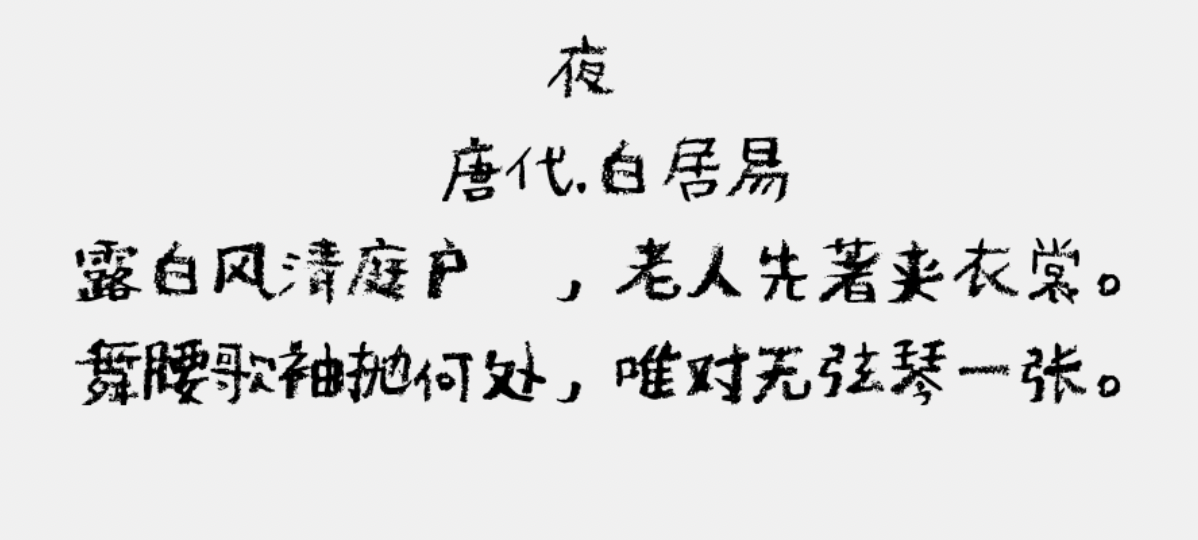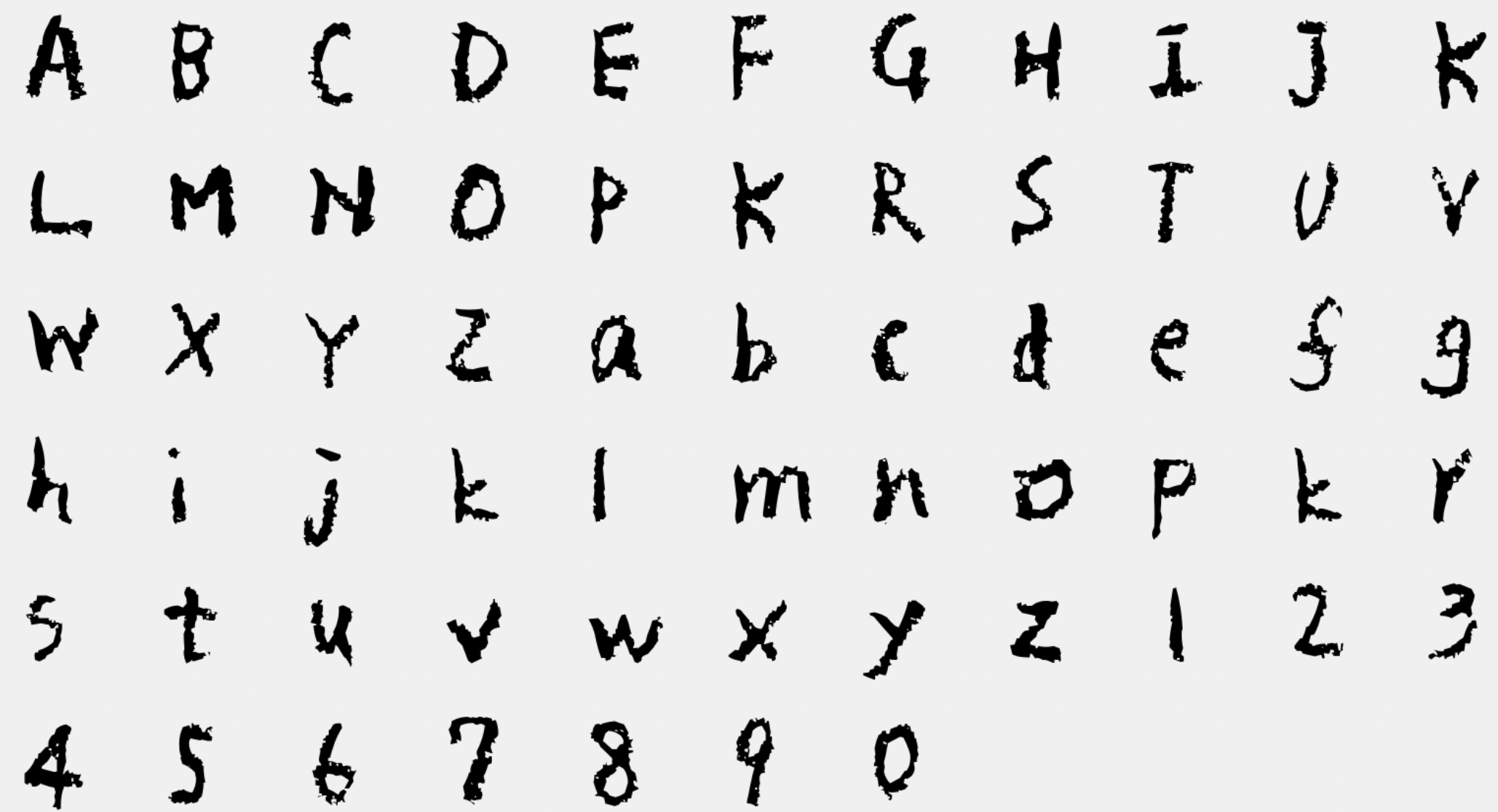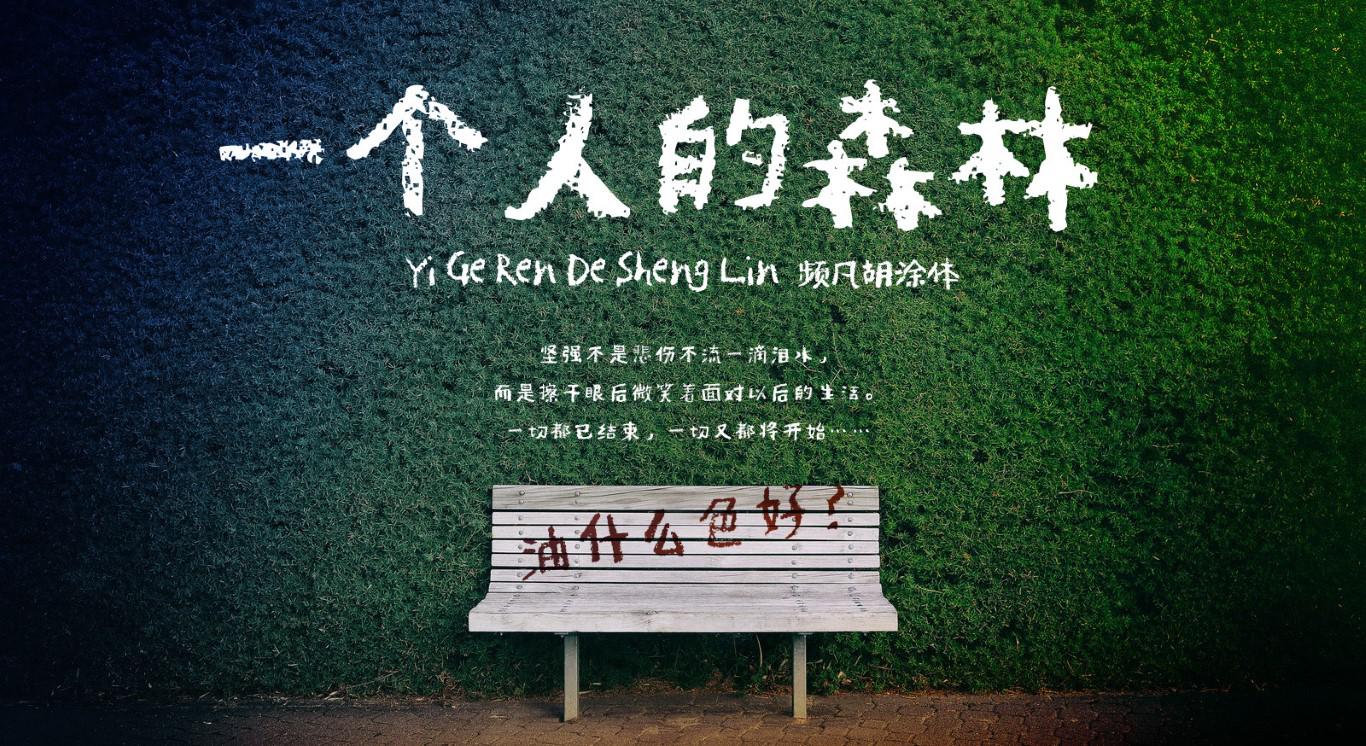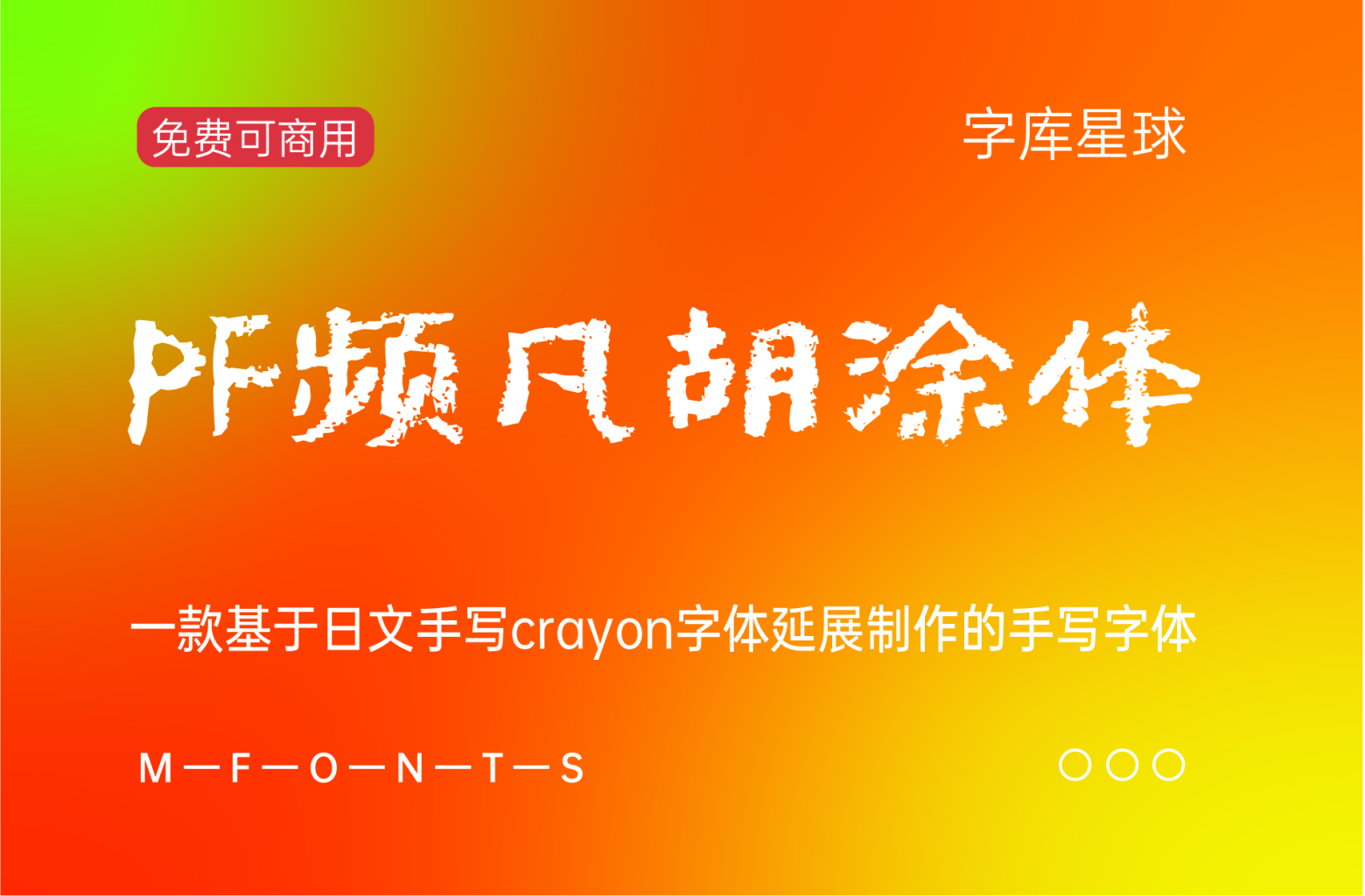
字体来源:给儿子生日制作画面标题时,偶然发现一款日文字体,频凡感觉非常适合。奈何整体完成度较低,只含括二千余汉字,且多为日系繁体字形。字体应用后愈加喜欢,相遇即有缘,权当一份未来的生日礼物,遂产生增补冲动。字体命名来源于自己中年对“难得糊涂”的理解及字体涂鸦的本身。
增补目标:一、支持简体中文编码——现代汉语常用字表(3500字),另按字频增加高频汉字及符号。二、支持GB/T 2312 汉字表(6763字),满足中文简体需求;发布1.0简体正式版。三、酌情补充常用繁体中文字符,满足国人中文简繁基础应用;发布2.0简繁正式版。
调整字形:原字随性浪漫,字符大小不一,更有“逼真的笔迹感”;但因此使用性非常有限,字符堆叠难予辨认,尤其不适合文本。基于设计感与阅读性的平衡,促进字体完成度,统一了字符宽高,逐字调整字符大小。同时,发现并修改原有日系字形,使其更加贴合简体中文规范和习惯。
字体展示
文章标题:PF频凡胡涂体